유명인의 싸인은 단순한 서명이 아니라, 그들의 브랜드와 아이덴티티를 담고 있어요. 잘 디자인된 싸인은 기억에 남고, 팬들에게도 특별한 의미를 가질 수 있어요! 🌟
내가 생각했을 때, 유명인의 싸인은 개성, 속도, 상징성을 갖추고 있어요. 이제 그들이 사용하는 싸인의 비밀을 하나씩 알아볼까요? 🚀
유명인 싸인이 특별한 이유 🌟
유명인의 싸인은 단순한 서명이 아니라, 그들의 개성과 상징을 담은 브랜드의 일부예요. 연예인, 스포츠 스타, 정치인, 기업가 등 유명한 인물들의 싸인은 팬들에게 특별한 의미를 가지며, 때로는 고가의 수집품으로 거래되기도 해요! ✍
🔹 왜 유명인의 싸인이 특별할까? ✔ 한눈에 알아볼 수 있는 개성적인 스타일 ✔ 빠르고 자연스럽게 쓸 수 있는 디자인 ✔ 자신만의 심볼이나 독특한 요소 포함 ✔ 브랜드 가치가 포함된 서명
📌 유명인 싸인의 특별한 요소 ✨
요소 설명 개성 있는 디자인 한눈에 알아볼 수 있도록 독창적인 스타일 빠른 작성 가능 팬 사인회 등에서 빠르게 싸인할 수 있도록 설계 기호나 심볼 포함 하트❤, 별⭐, 화살표➡ 같은 아이콘 활용 브랜드화 가능 이름 자체가 브랜드가 되는 경우 (예: 나이키 창업자의 싸인) 이제 유명한 싸인의 공통점을 분석해볼까요? 🔎
유명한 싸인의 공통점 분석 🔎
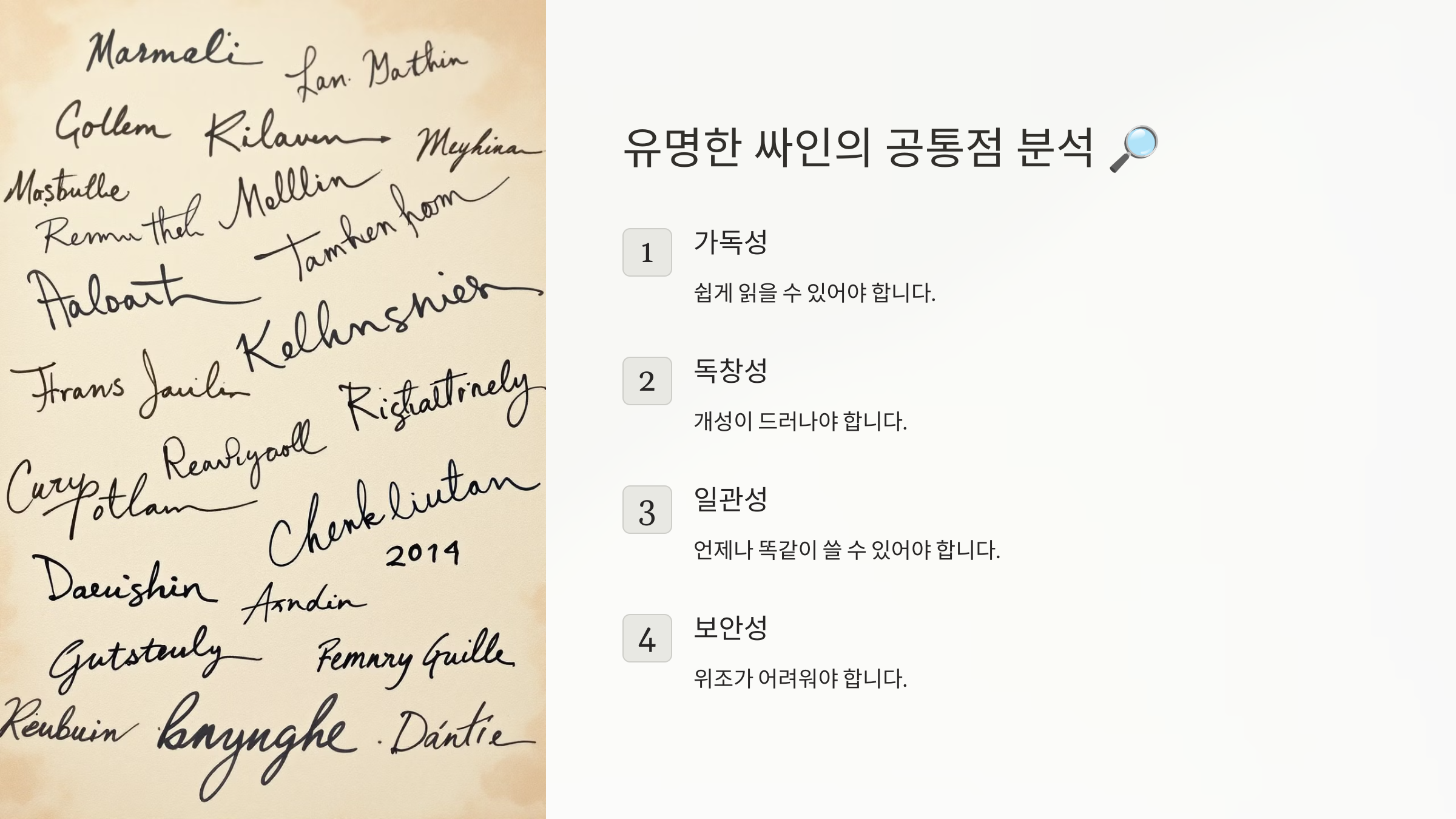
전 세계 유명한 인물들의 싸인을 보면, 몇 가지 공통적인 특징이 있어요. 그들의 싸인은 단순한 이름이 아니라, 브랜드화된 개성을 담고 있어요! ✍
🔹 유명한 싸인의 공통점
✔ 한눈에 알아볼 수 있도록 독창적인 디자인
✔ 빠르게 써도 흐름이 자연스러운 필기체 스타일
✔ 자신만의 기호(⭐, ❤, 🎵 등)를 추가하여 개성 표현
✔ 이름의 특정 부분을 강조하거나 변형하여 브랜드화
📌 유명한 싸인의 핵심 요소 💡
공통점 설명 독창적인 디자인 일반적인 글씨체가 아닌, 개성이 강한 스타일 자연스러운 필기체 흐름이 끊기지 않고 부드럽게 이어짐 기호나 심볼 추가 하트❤, 별⭐, 악보🎵 등의 장식 포함 브랜드화 가능 이름 자체가 상징이 되어 브랜드로 자리 잡음 이제 연예인과 스포츠 스타의 싸인 특징을 살펴볼까요? 🏆
연예인과 스포츠 스타 싸인의 특징 🏆
연예인과 스포츠 스타의 싸인은 팬들에게 특별한 의미를 가지는 상징적인 요소예요. 사인회나 팬미팅에서 많이 사용되기 때문에 빠르게 작성하면서도 개성이 살아 있어야 해요. ✍
🔹 연예인 & 스포츠 스타 싸인의 공통점
✔ 이름의 특정 글자를 강조하여 디자인
✔ 별⭐, 하트❤, 음악🎵 같은 기호 포함
✔ 싸인의 끝부분을 곡선이나 긴 선으로 마무리
✔ 자신만의 로고처럼 브랜드화한 스타일
📌 연예인 & 스포츠 스타 싸인의 특징 🎤⚽
스타일 특징 대표적인 예 이니셜형 싸인 짧고 강렬한 이니셜을 활용 BTS RM, 크리스티아누 호날두 (CR7) 기호 포함 싸인 하트❤, 별⭐, 음악🎵 같은 기호 활용 방탄소년단, 블랙핑크, 축구 선수 메시 강조형 싸인 특정 글자를 강조하여 크게 씀 마이클 조던, 손흥민 이제 정치인과 기업인의 싸인 스타일을 살펴볼까요? 🏛
정치인과 기업인의 싸인 스타일 🏛
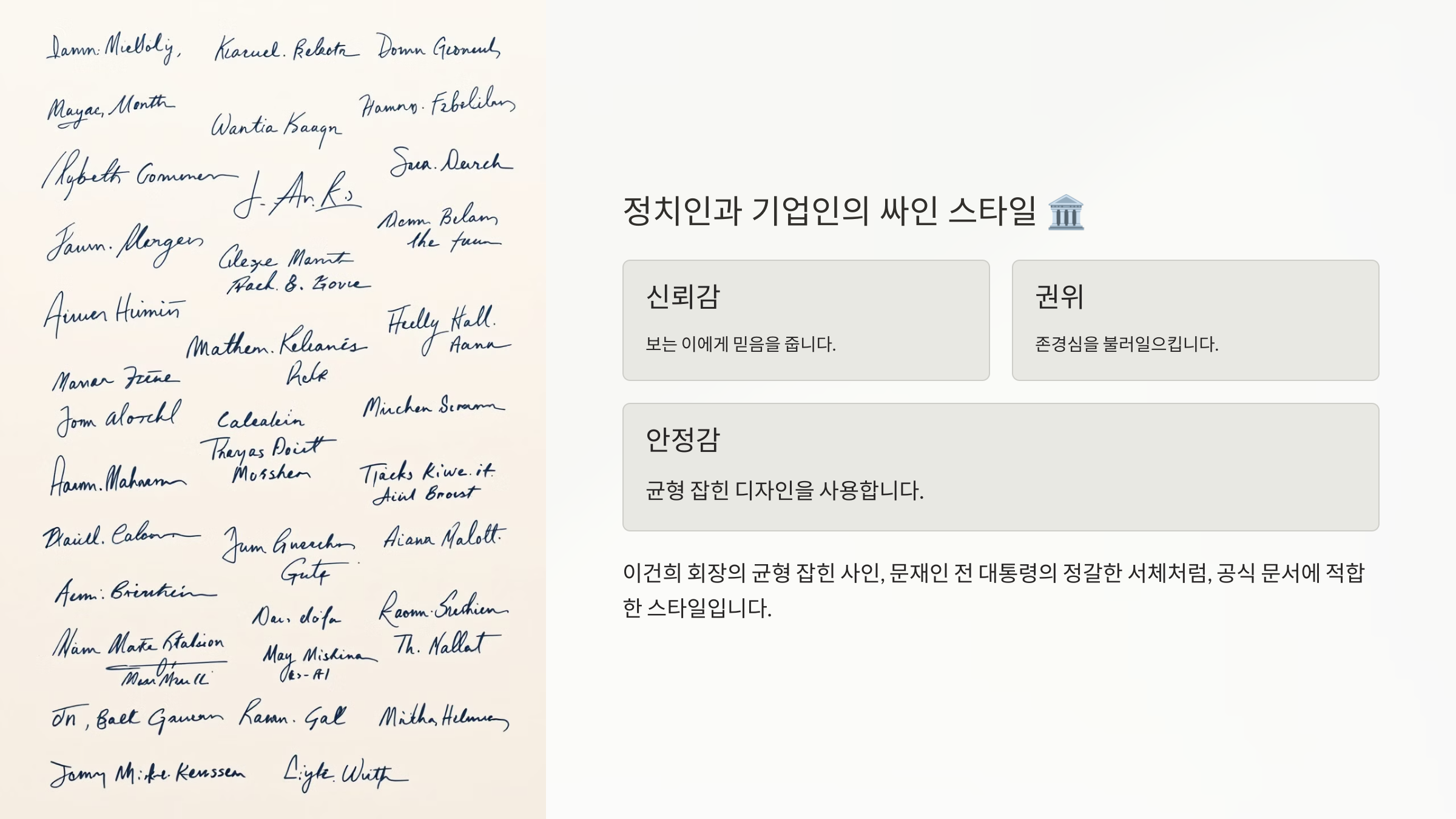
정치인과 기업인의 싸인은 공식 문서나 법적 서류에서 자주 사용되기 때문에 신뢰감을 주는 스타일이 많아요. 이들의 싸인은 전문적이고 권위 있는 느낌을 주면서도 빠르게 작성할 수 있어야 해요. ✅
🔹 정치인 & 기업인의 싸인의 특징
✔ 흐름이 자연스러운 필기체 스타일
✔ 직선과 곡선을 적절히 조합하여 빠르게 작성 가능
✔ 이름 전체를 쓰거나, 이니셜을 강조하는 형태
✔ 문서에서 신뢰감을 줄 수 있는 안정적인 디자인
📌 정치인 & 기업인의 싸인 스타일 분석 ✍
스타일 특징 대표적인 예 필기체 스타일 자연스럽고 우아한 흐름 버락 오바마, 빌 게이츠 이니셜 강조형 이름의 첫 글자를 강조 도널드 트럼프, 일론 머스크 단순 직선형 간결하면서도 권위적인 느낌 워런 버핏, 마크 저커버그 이제 예술가와 디자이너의 독창적인 싸인을 알아볼까요? 🎨
예술가와 디자이너의 독창적인 싸인 🎨
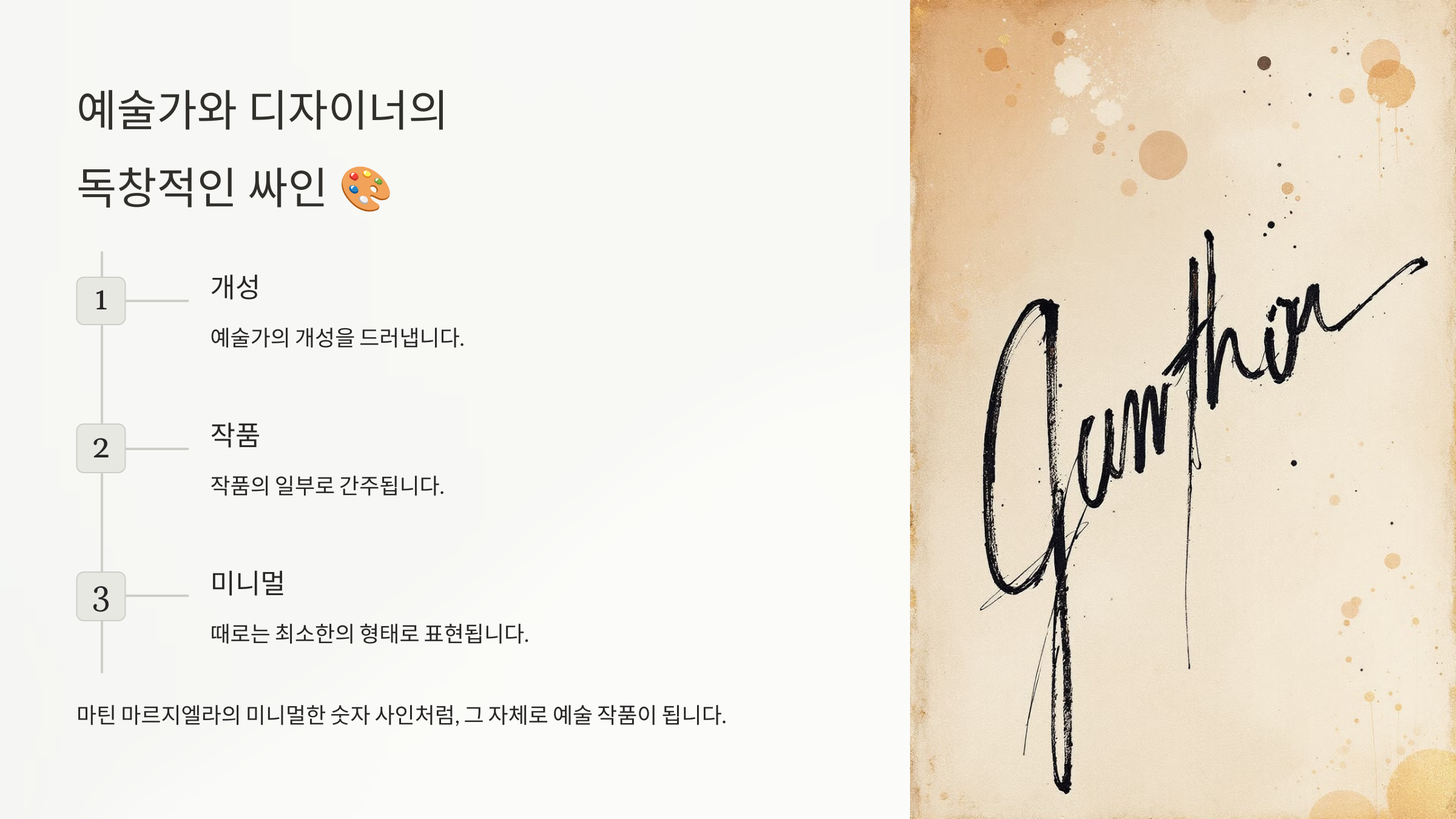
예술가와 디자이너의 싸인은 하나의 예술 작품처럼 개성이 강한 경우가 많아요. 특히, 그림을 그리거나 로고처럼 활용되는 싸인이 많으며, 시각적으로도 독특한 형태를 띠어요. ✍
🔹 예술가 & 디자이너 싸인의 특징
✔ 자신만의 독창적인 서체 활용
✔ 필기체와 그래픽 요소를 조합한 스타일
✔ 서명에 작은 그림(붓, 팔레트, 아이콘 등) 추가
✔ 브랜드 로고처럼 활용 가능
📌 예술가 & 디자이너 싸인의 특징 🎭
스타일 특징 대표적인 예 개성적인 필기체 독창적인 흐름을 가진 서체 빈센트 반 고흐, 파블로 피카소 그래픽 포함형 서명에 작은 그림 요소 포함 살바도르 달리, 키스 해링 로고형 싸인 브랜드 로고처럼 활용 가능 카를 라거펠트, 버질 아블로 이제 유명인 싸인처럼 만드는 방법을 알아볼까요? 🚀
유명인 싸인처럼 만드는 방법 🚀
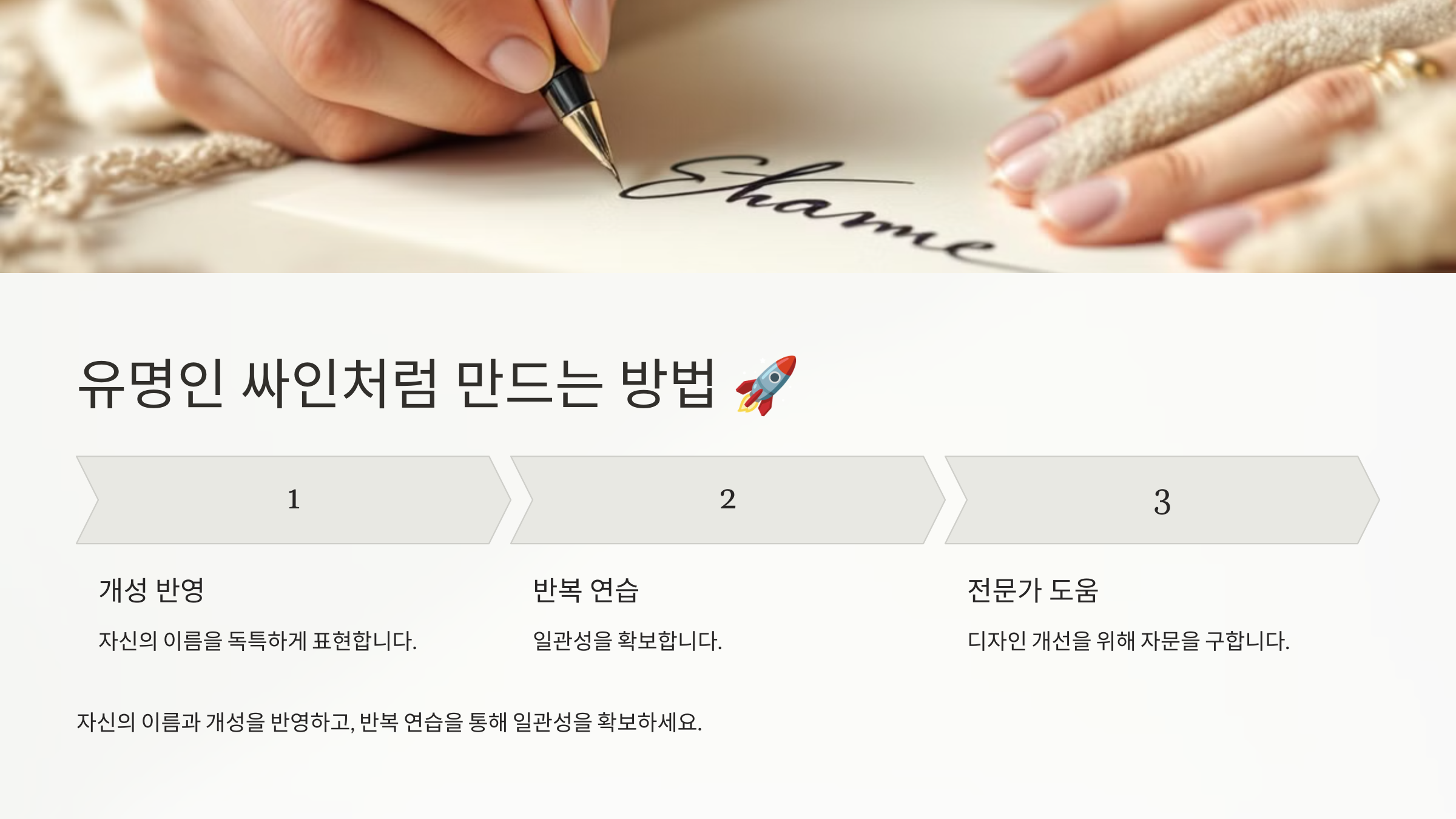
유명인들의 싸인은 단순한 서명이 아니라, 하나의 브랜드처럼 활용돼요. 이제 그들의 싸인에서 배운 요소를 활용해 나만의 멋진 싸인을 만들어볼까요? ✍
🔹 유명인 싸인처럼 만드는 5단계
1. 싸인의 기본 형태 정하기 (이니셜 vs 풀네임)
2. 흐름이 자연스러운 필기체 연습
3. 기호(⭐, ❤, 🎵)나 특별한 요소 추가
4. 싸인의 끝부분에 포인트 주기 (긴 선, 곡선 등)
5. 빠르고 일관되게 쓸 수 있도록 연습하기
📌 유명인 싸인 스타일 연습법 ✍
단계 설명 기본 형태 정하기 이니셜형, 필기체형, 기호형 중 선택 자연스러운 필기체 부드럽고 연결된 필기체 스타일 연습 기호 추가 ⭐, ❤ 같은 기호를 활용하여 개성 강조 끝부분 마무리 긴 선이나 곡선을 활용하여 마무리 반복 연습 빠르고 일관되게 싸인을 연습 이제 싸인에 대한 궁금증을 해결할 시간! FAQ에서 자주 묻는 질문을 정리해 볼까요? ❓
FAQ ❓
Q1. 유명인 싸인은 왜 특별한가요?
A1. 유명인의 싸인은 브랜드화된 상징이기 때문이에요. 팬들이 쉽게 기억할 수 있고, 빠르게 작성할 수 있으면서도 개성이 살아 있는 스타일로 디자인되어 있어요. ✍
Q2. 싸인을 빠르게 연습하는 방법은?
A2. 효과적인 연습법은 다음과 같아요: 1⃣ 눈 감고 싸인 연습 (손의 감각 익히기) 2⃣ 다양한 크기로 싸인 연습 (A4, 명함, 포스트잇) 3⃣ 빠른 속도로 싸인 연습 (5초 이내에 완성 목표) 4⃣ 거울을 보며 싸인 확인 (다른 사람이 볼 때 느낌 체크)
Q3. 싸인을 바꿔도 괜찮을까요?
A3. 싸인을 바꾸는 것은 가능하지만, 일관성이 중요해요. 공식 문서나 계약서에서 사용되는 싸인은 자주 바꾸지 않는 것이 신뢰도를 유지하는 데 좋아요. ✅
Q4. 싸인에 기호(하트, 별 등)를 넣어도 괜찮나요?
A4. 네! 기호를 넣으면 개성이 강조되고, 더욱 기억에 남는 싸인이 될 수 있어요. 하지만 너무 많은 기호를 넣으면 복잡해 보일 수 있으니 적절히 활용하는 것이 좋아요. ⭐❤⚡
Q5. 유명한 싸인을 참고해서 만들어도 될까요?
A5. 참고하는 것은 가능하지만, 완전히 똑같이 따라 하는 것은 추천하지 않아요. 자신만의 개성을 반영하여 이니셜, 필기체, 기호 등을 조합해 독창적인 싸인을 만들어보세요. 🎨
Q6. 싸인의 크기는 어느 정도가 적당한가요?
A6. 싸인은 너무 크면 문서에서 공간을 많이 차지하고, 너무 작으면 가독성이 떨어질 수 있어요. A4 용지, 명함, 포스트잇 등 다양한 크기로 테스트하면서 적절한 크기를 찾는 것이 좋아요. 📏
Q7. 디지털 싸인을 만들려면 어떻게 해야 하나요?
A7. 태블릿이나 스마트폰에서 스타일러스 펜을 이용해 싸인을 작성한 후 PNG 파일로 저장하면 활용할 수 있어요. Adobe Sign, DocuSign 같은 전자 서명 도구도 유용해요. 💻
Q8. 싸인을 멋있게 보이게 하는 가장 쉬운 방법은?
A8. 싸인을 더 멋지게 만들려면,
✅ 첫 글자에 포인트를 주기
✅ 끝 부분을 길게 마무리하기
✅ 기호나 심볼을 추가해 개성을 살리기
✅ 일관성을 유지하면서 빠르게 싸인하기 이런 요소를 추가하면 더욱 세련된 싸인이 완성돼요! ✨
이제 싸인 만들 때 실수하지 않고, 완벽한 나만의 싸인을 완성할 수 있겠죠? 🚀 꾸준히 연습해서 멋진 싸인을 만들어보세요! ✨